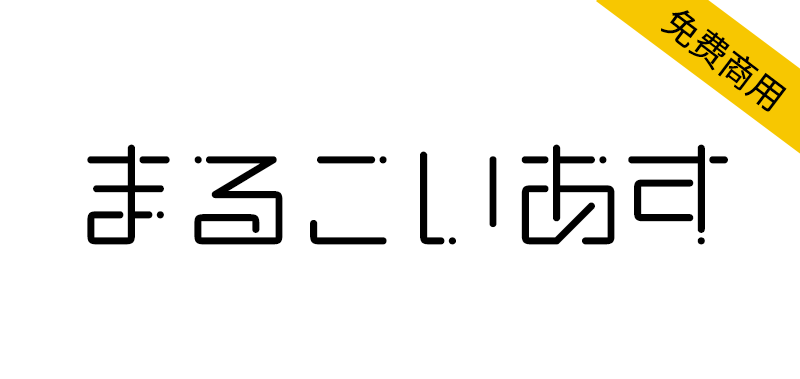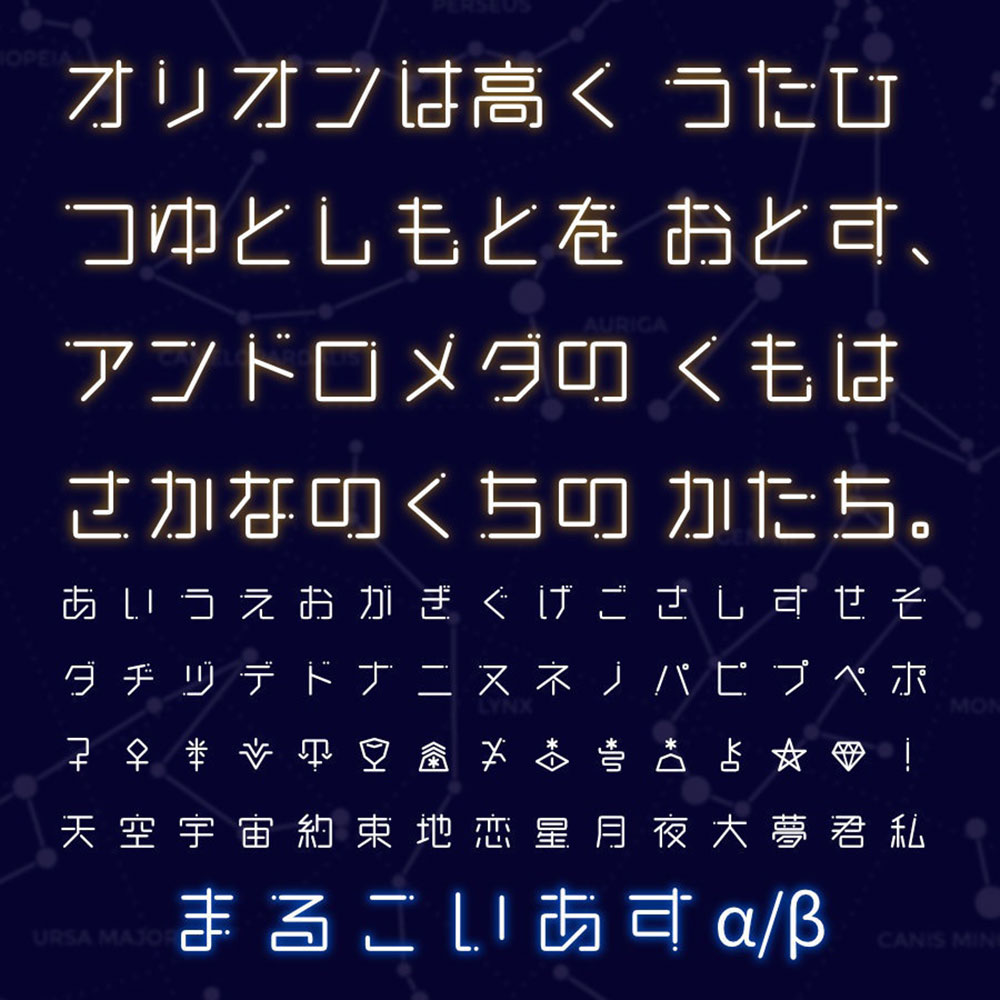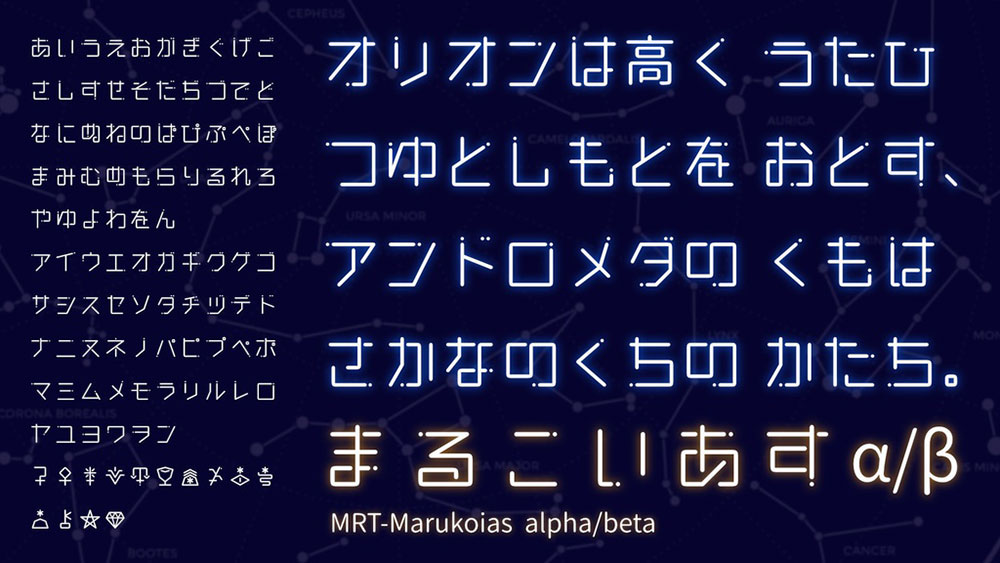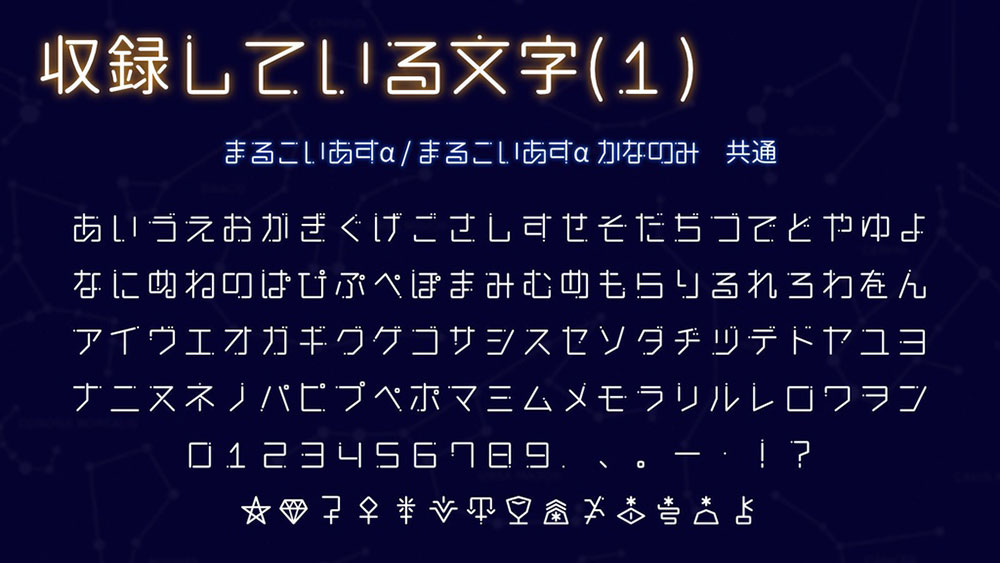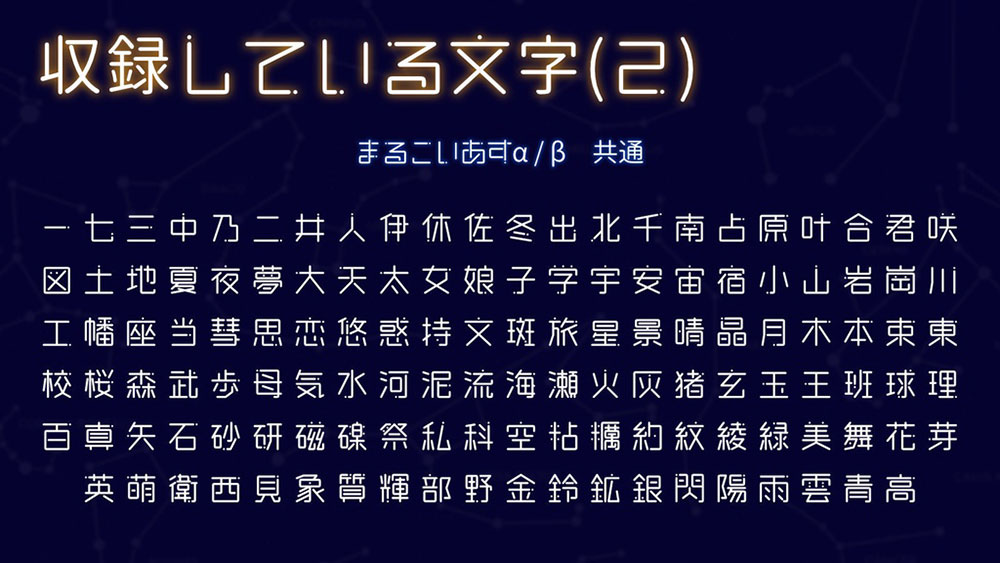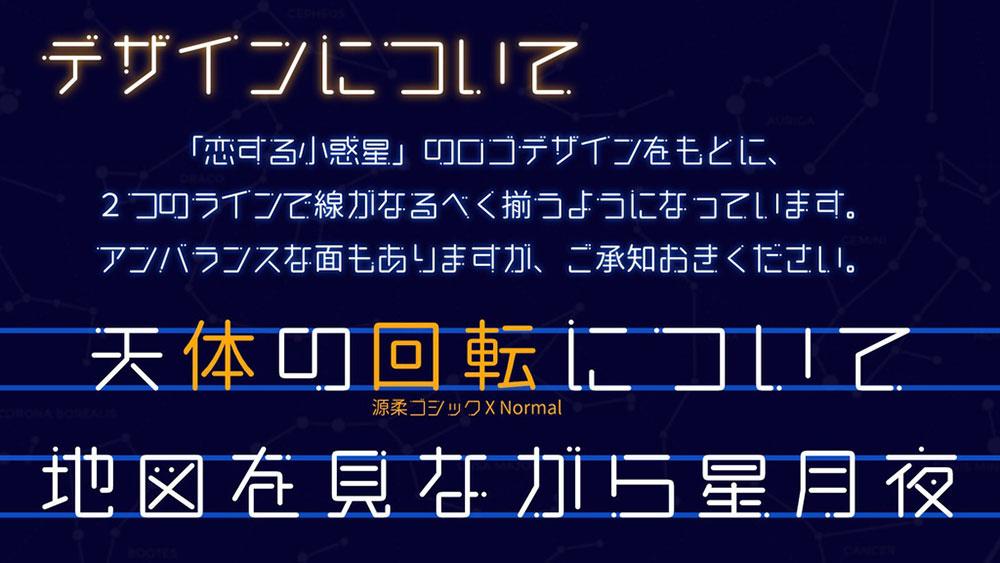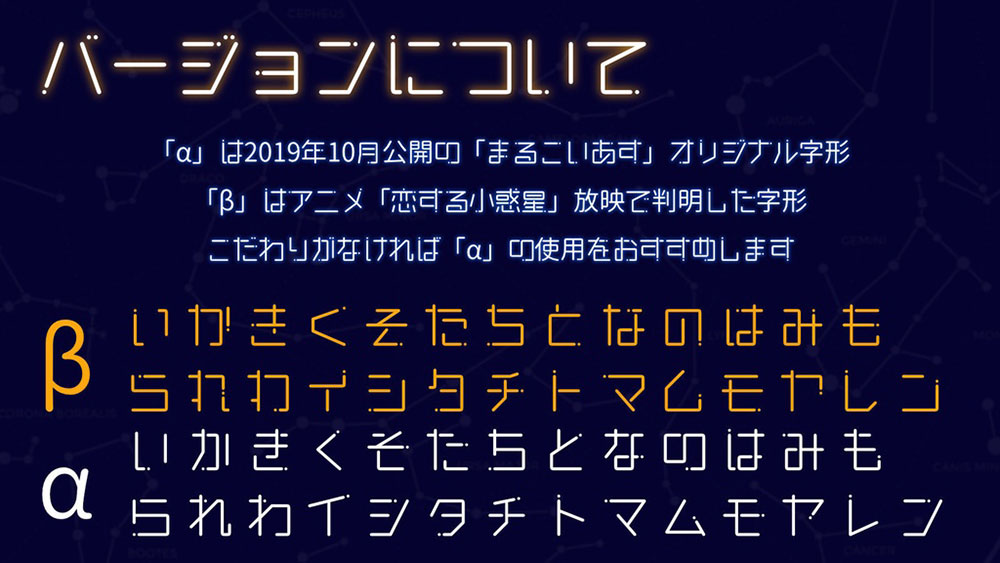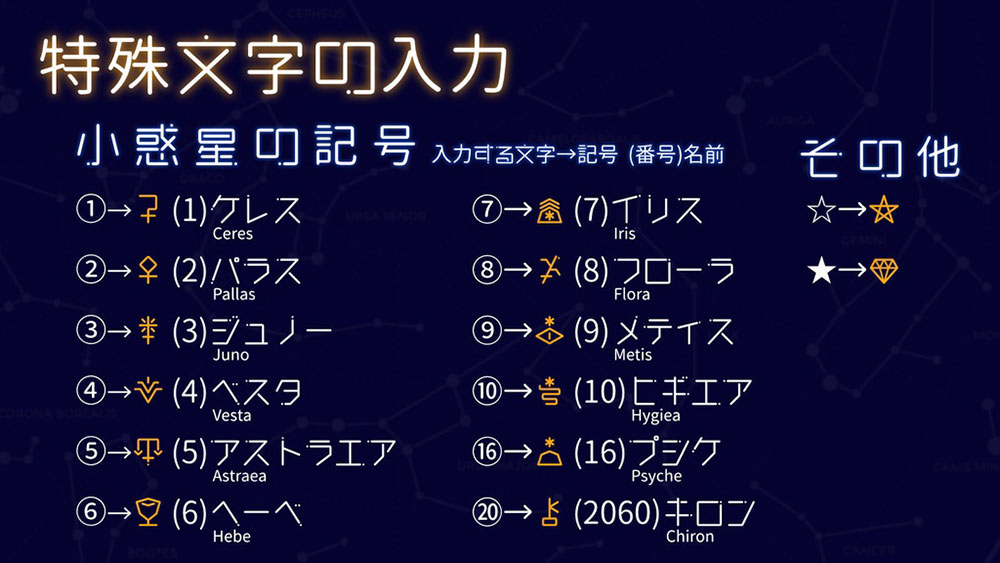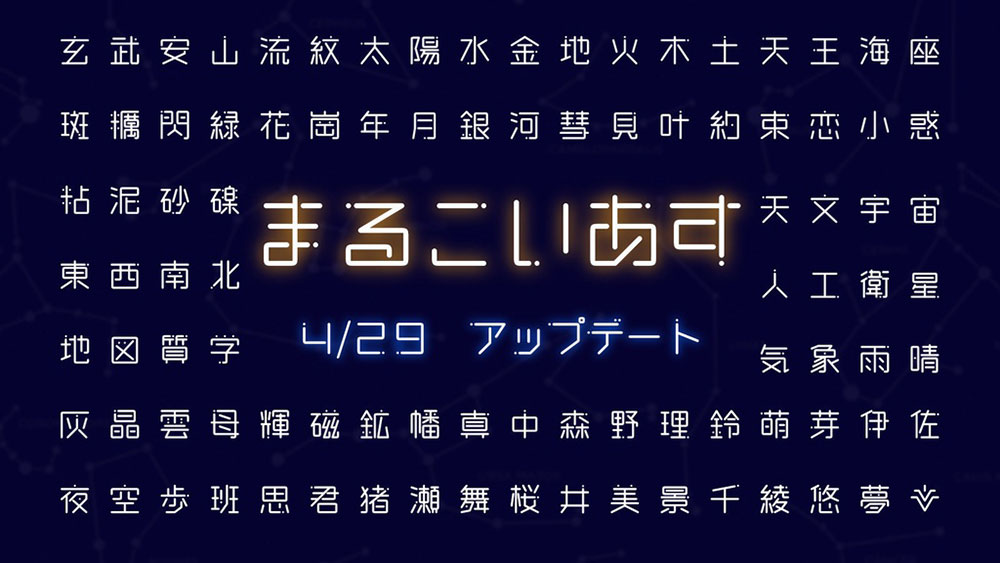
恋星圆体(まるこいあす)是参考漫画/动画《恋爱的小行星》的标志制作的。下边缘和上边框对齐,虽然是直线但是有圆形的字体。与“小行星”有关,还收录了表示小行星的天文符号。
「まるこいあす」は、漫画/アニメ「恋する小惑星」のロゴを参考して制作しました。下辺と上部で横線が揃う、直線的だけど丸みのあるフォントです。「小惑星」にちなみ、小惑星を表す天文記号も収録しています。